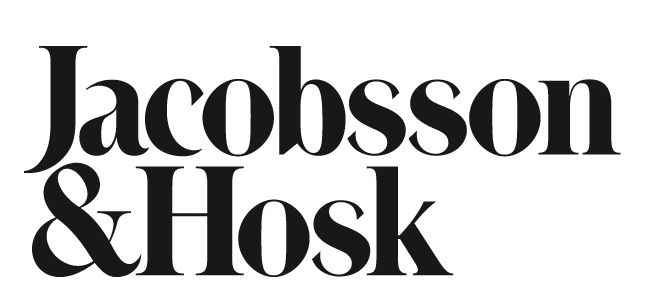
Wer kennt diese Schrift?
Fast ganz genau ist es die ITC Toms Roman. Das "c" könnte aber auch mundgebissen sein … und das "&" auch. Aber vielleicht gibt es ja mehrere, ich kenne den Font nicht wirklich.